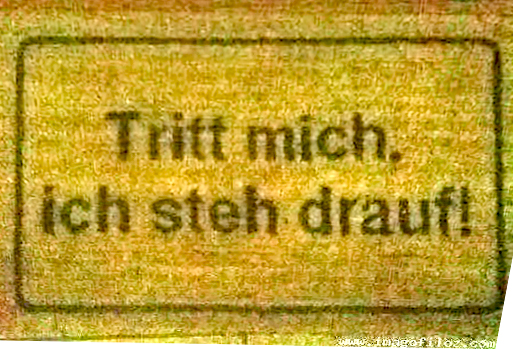
Suche Schriftart für Fußmatte!
ich möchte selbst eine Fußmatte gestalten für jemanden, der ein ziemlicher Typonerd ist. Möglichst sollte sie ganz genauso aussehen wie die Schrift, die auf dem folgenden Foto verwendet wurde (sorry für die miese Quali), denn ich möchte auch den gleichen Text verwenden.
Weiß jemand, wie diese Schrift heißt? Falls sie kostenpflichtig ist, gibt es eine kostenlose, die ähnlich ist?
Ich dachte erst an Arial Narrow, aber da stimmt das Ausrufezeichen nicht...
ich hab das mal entzerrt…
Würde mich auch interessieren, wer dieser "T" ist, der da jemanden ritt… :mrgreen::peng:
tritt? oder trete?
versuch mal univers oder tret gothic ähhh 'trade gotic'. kostenlos gibts die aber nicht.
warum muss es denn die gleiche schrift sein, arial narrow geht sicher auch und merkt keiner.
Vielen Dank! Es heißt "Tritt", und ich schätze mal, der Punkt ist ein Komma... (schlecht zu sehen).
Von wegen "merkt keiiner" - jemand, der Arial hasst, wird das leider ganz sicher merken...
Univers oder 'trade gotic', gibt's da vielleicht auch 'ne ähnliche Schrift, die kostenlos ist, und nicht Arial?
Wieso muss es denn so ähnlich sein? Du kannst doch eigentlich auch eine ganz andere Schrift nehmen, oder? :tutor:
danke für eure Antworten. Die Schriften werd ich mir auf jeden Fall merken. Durch Zufall hab ich genau diese Fußmatte heute, als ich eine Blanko-Matte kaufen wollte, im Baumarkt gefunden... (und im Internet vergeblich gesucht...).
Zumindest brauche ich nun nicht mehr zu malen :-)
… Zumindest brauche ich nun nicht mehr zu malen …
Das würde mich jetzt aber doch mal interessieren, wie Du Dir das vorgestellt hattest, die Schrift auf die Blancomatte zu bekommen. Du suchst eine Rechnerschrift … Du willst malen … ich krieg das nicht so ganz zusammen.